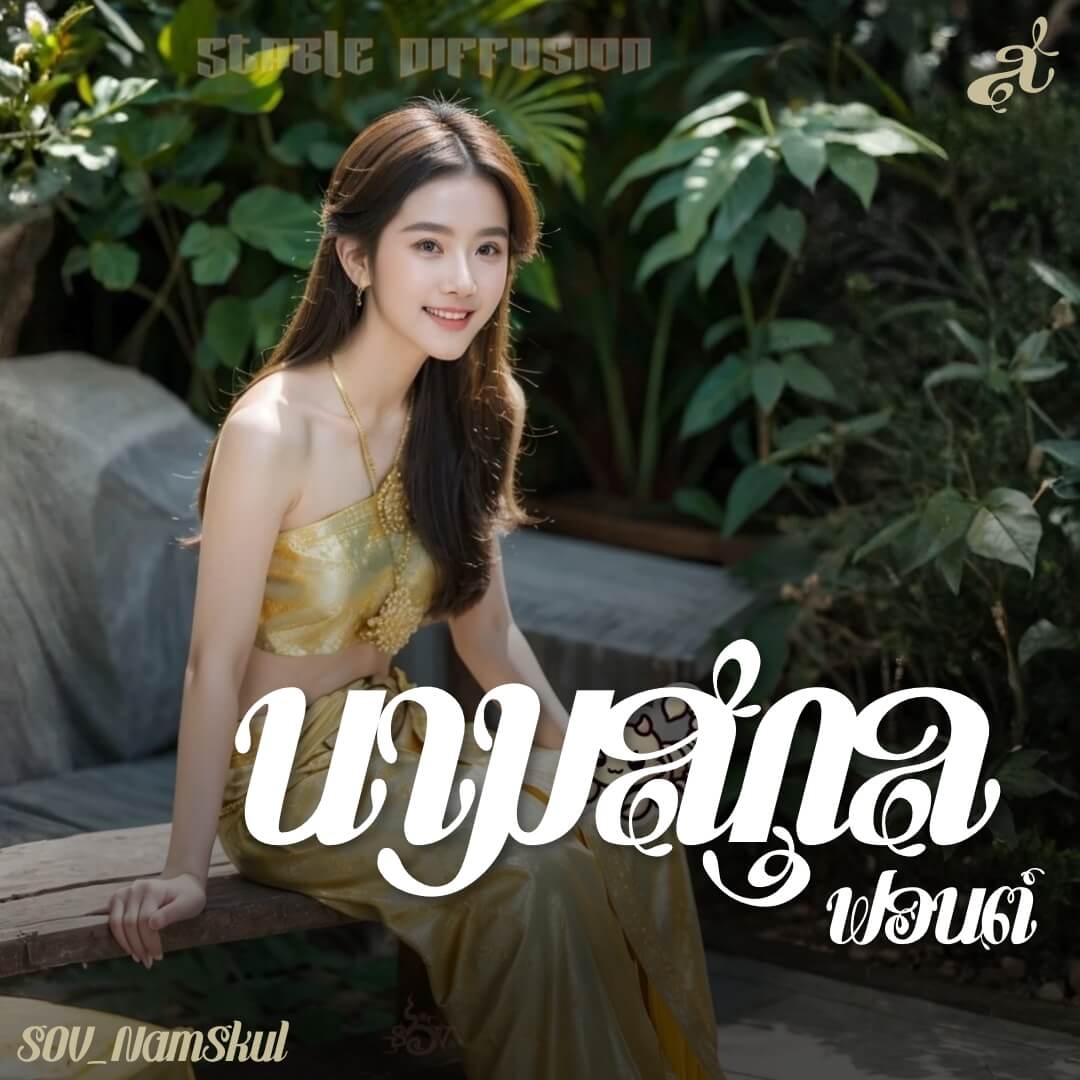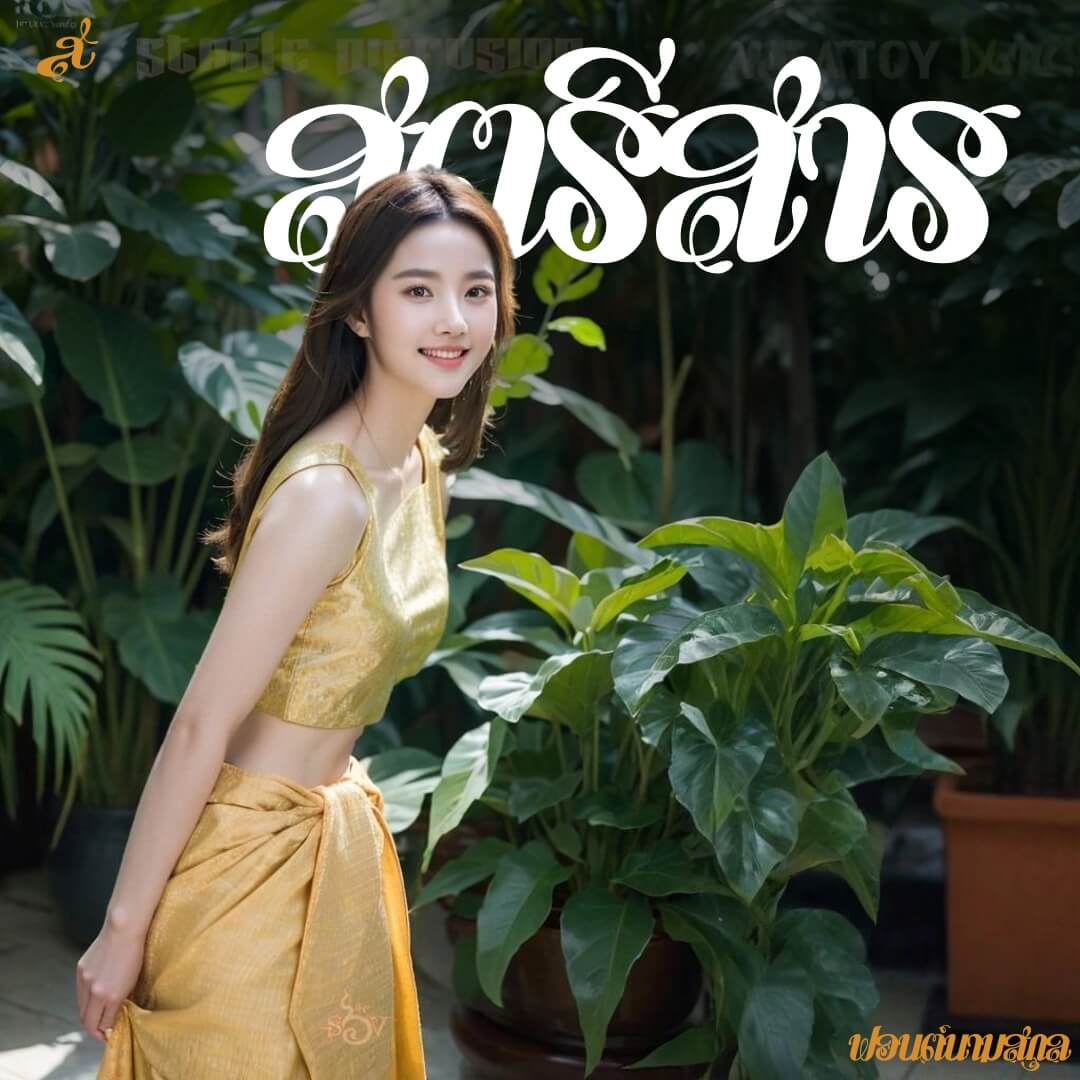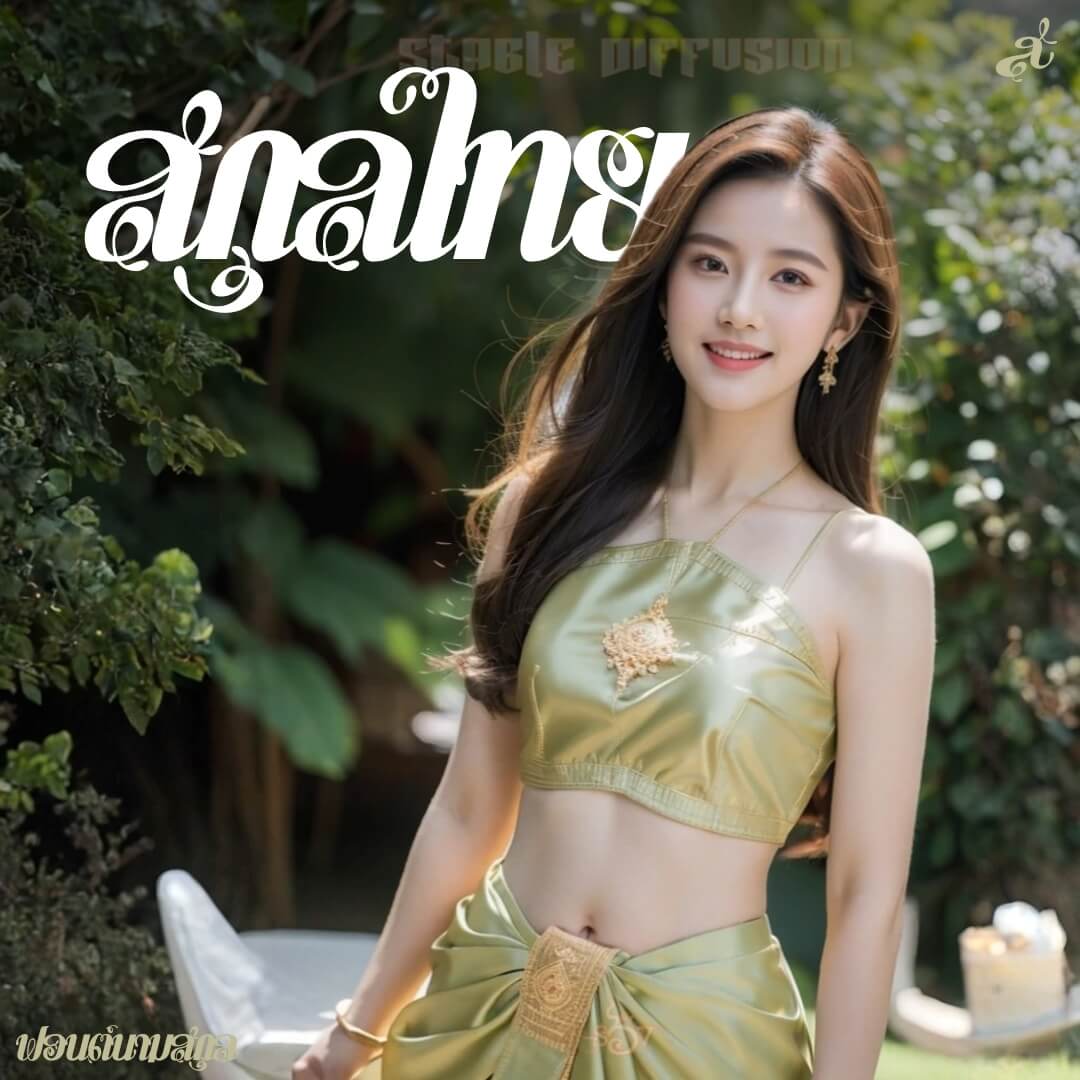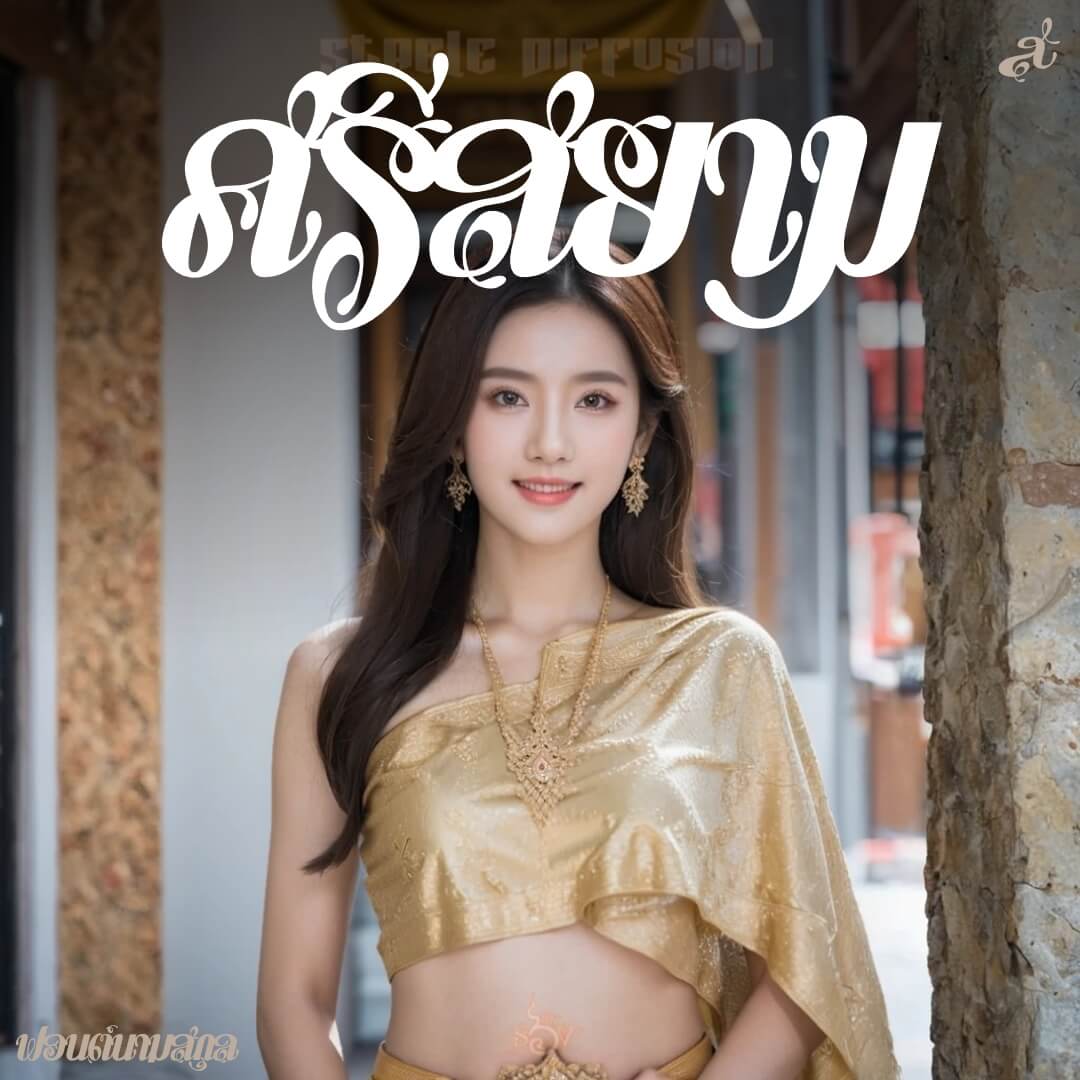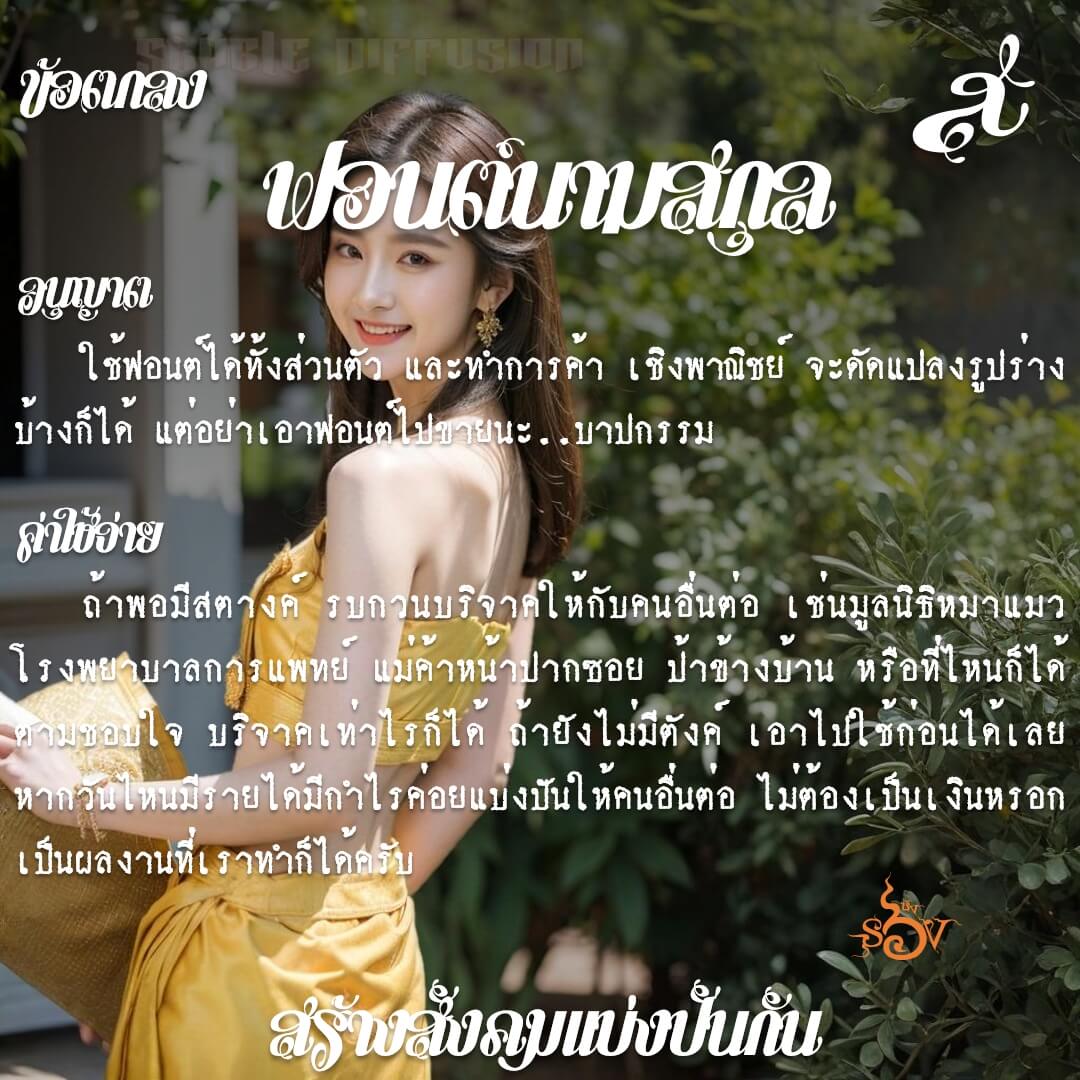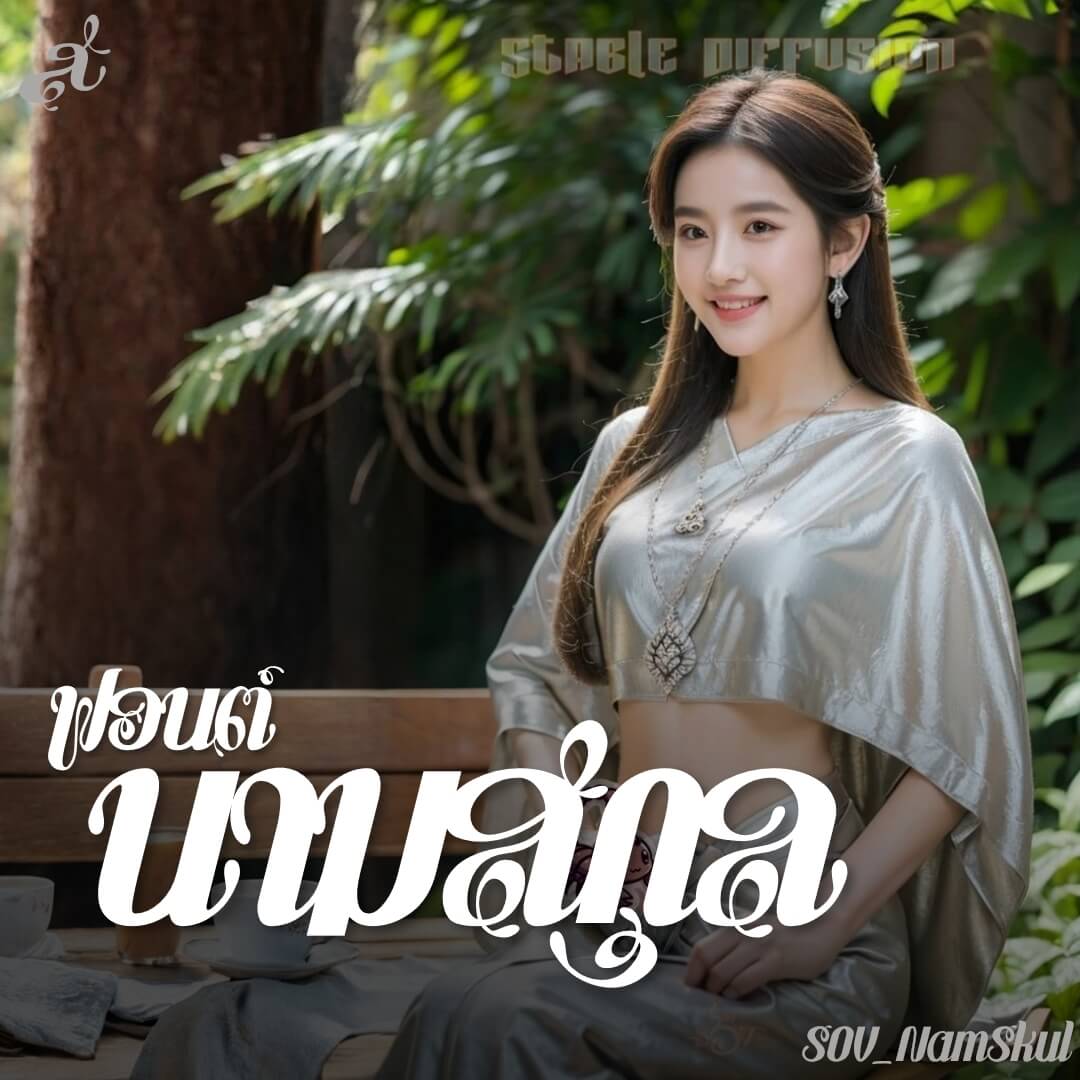
ฟอนต์นามสกุล ต้นทางจากป้ายเหล็กคำว่า “สกุล” ตัวเกยกัน เหมาะสำหรับใช้เป็นพาดหัว
สำหรับตัวพิเศษ ให้ใช้ ฯฯ นำหน้าตัวอักษร
เบื้องหลังการออกแบบ : ฟอนต์ นามสกุล
นามสกุล (SOV_NamSkul)